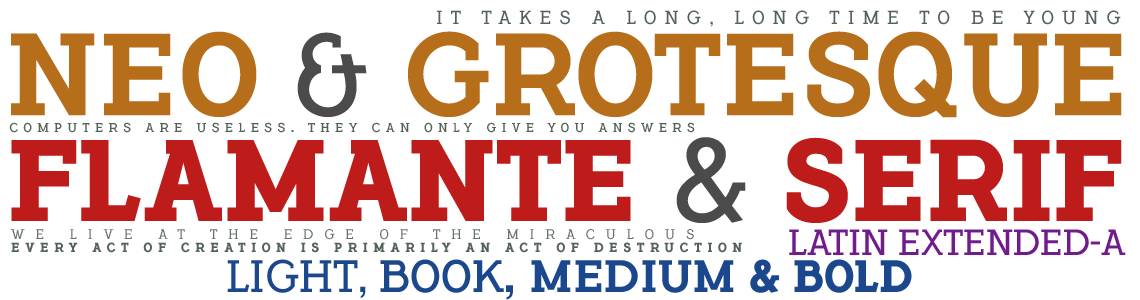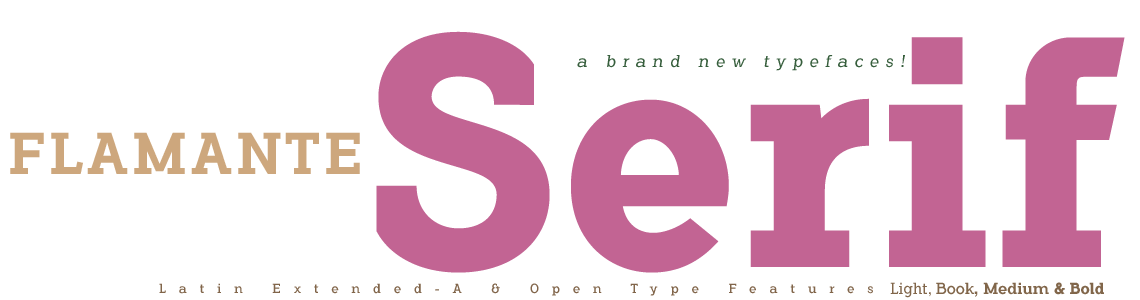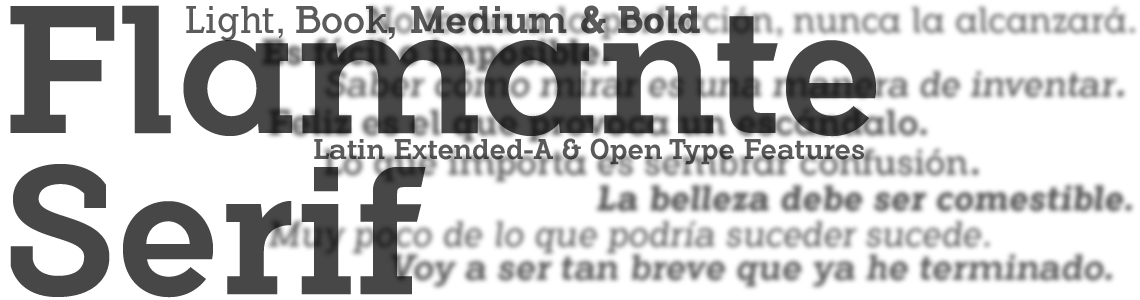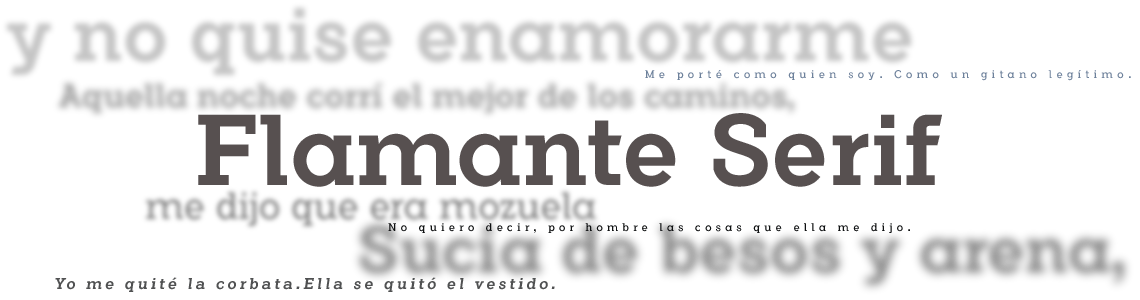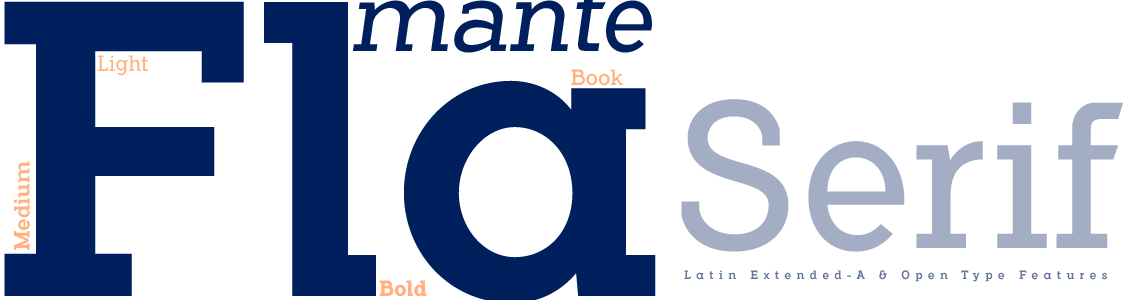
Incluyen el símbolo del Bitcoin: b# (b # )
Flamante Family Fonts -5 estilos-
-Serif- • -Sans- • -SemiSlab- • -Stencil- • -Round-.
Serif Family Fonts
Estilo: Serif, Geométrica, Slab, Corporativa
Proporción: Light, Book, Medium, Bold, Italic
Glyphs: 500
Autor: deFharo
Funciones OpenType: Additional languages, All Alternates, Alternate Annotation Forms, Capital Spacing, Denominators, Discretionary Ligatures, Extended Fractions, Historical Forms, Historical Ligatures, Inferiors, Kerning, Localized Forms, Numerators, Oldstyle Figures, Ordinals, Scientific Inferiors, Slashed Zero, Standard Ligatures, Subscript, Superior letters, Superiors, Superscript.